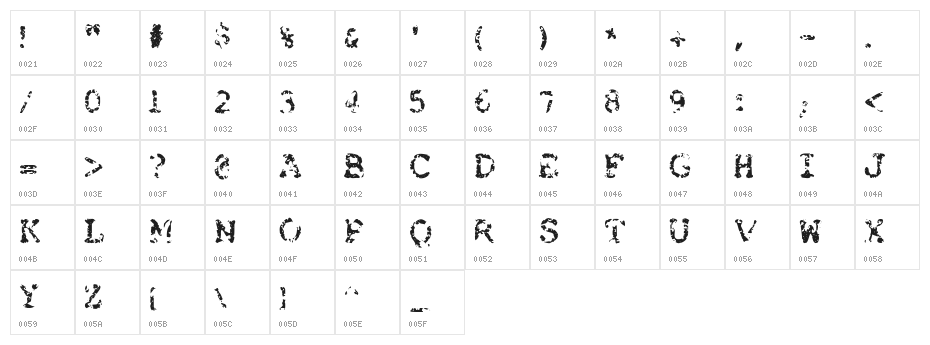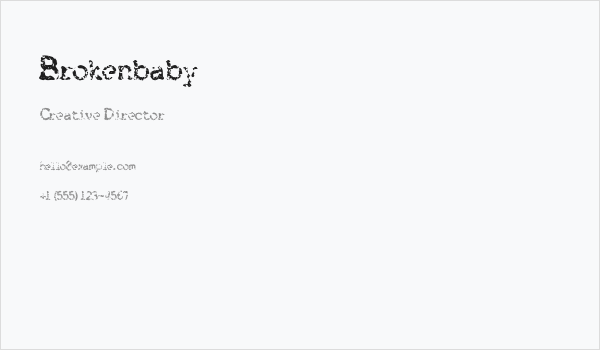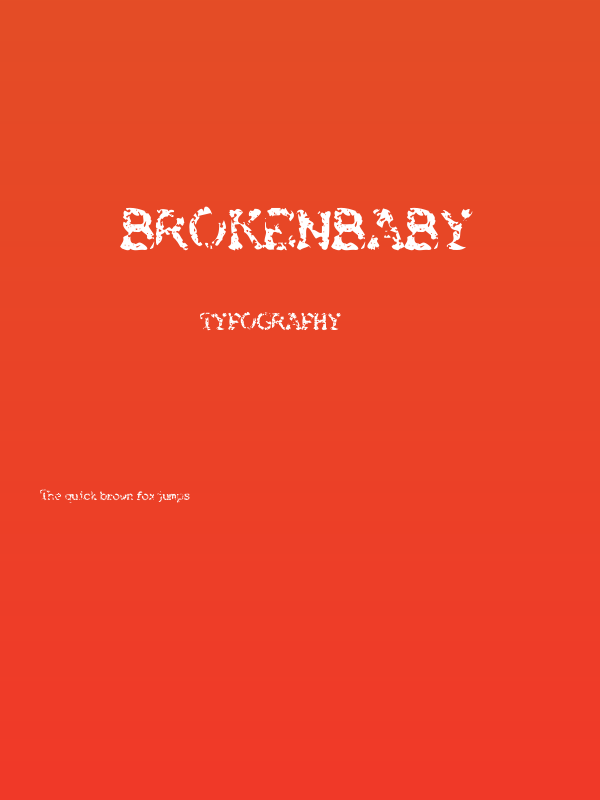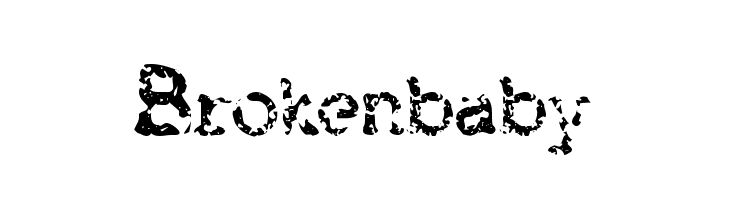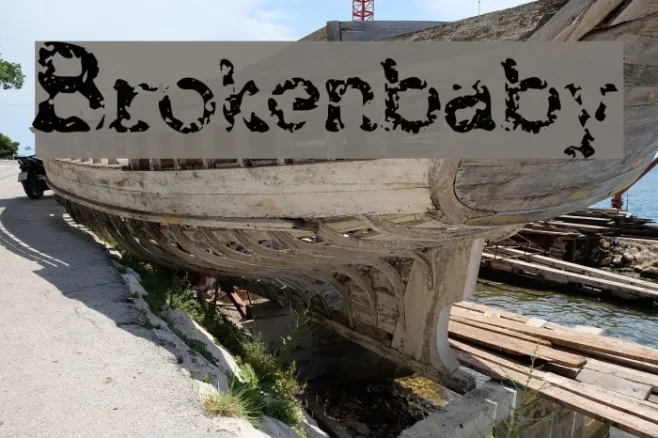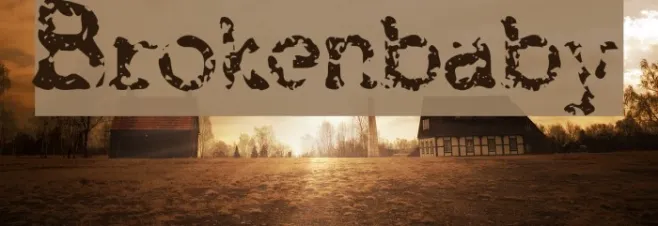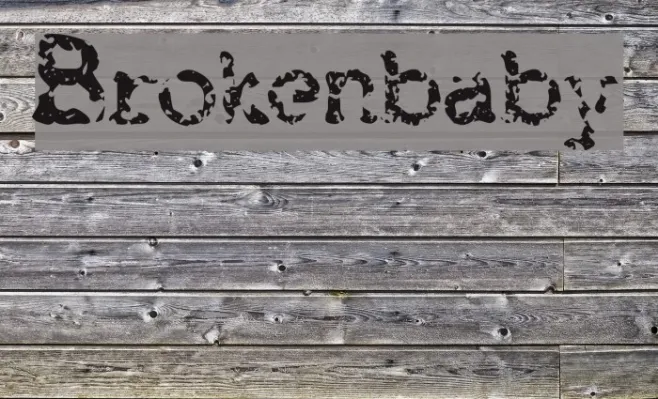
Brokenbaby Font
| Gesamtstil | Vintage |
| Vorgeschlagene Projekte | Ideal for projects requiring a vintage or industrial theme, such as posters, album covers, or branding for edgy products. |